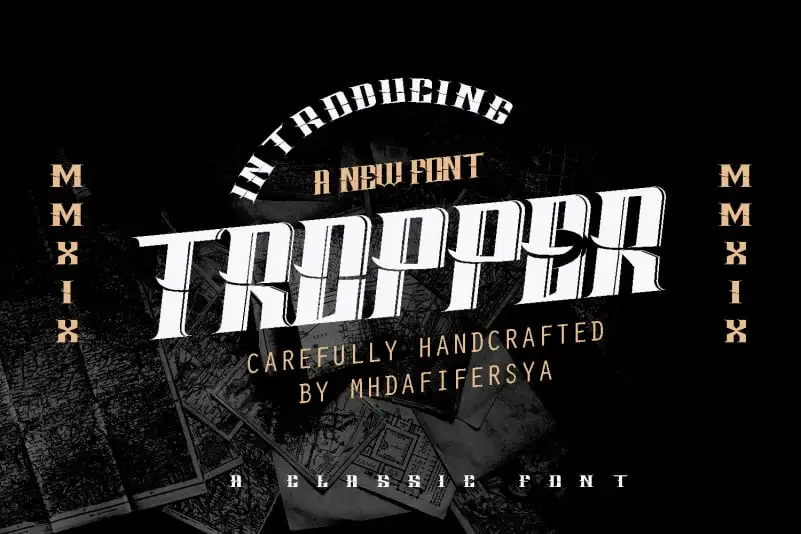
Tropper Typeface – Download Grátis
A fonte Tropper Typeface é uma família sans serif para ambientes de publicação e design editorial, projetada para se adaptar a diversas necessidades de design. Seu moderno e casual design torna-a perfeita para destaque, logomarcas e qualquer projeto que exija um estilo leve e elegante. Embora seja principalmente criado para headlines, também oferece uma leitura agradável para o texto do corpo da página, tornando-o ideal para designers gráficos em busca de uma fonte versátil e moderna. Esta fonte é perfeitamente adaptada para uso em magazines, sites web e até mesmo aplicativos móveis. Com seu design sofisticado e leitura agradável, Tropper Typeface certamente trará um toque único à sua próxima publicação ou projeto de design.
Designer: mhdafifersya